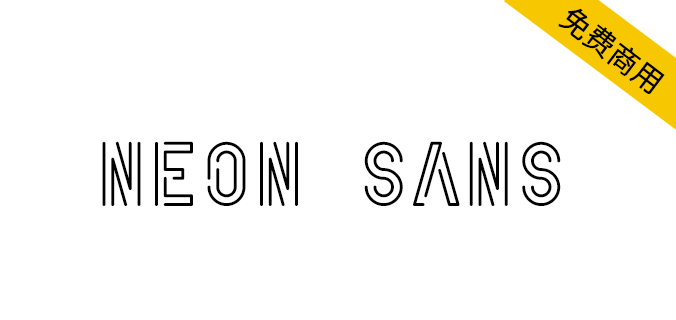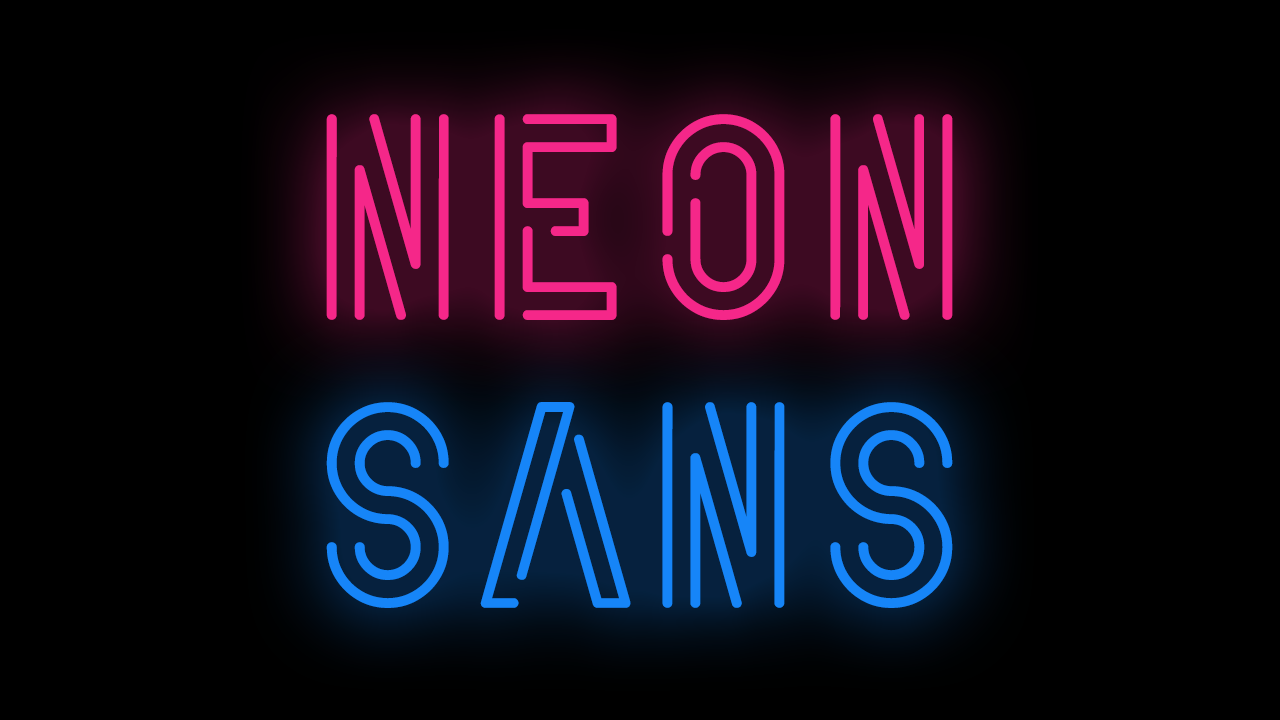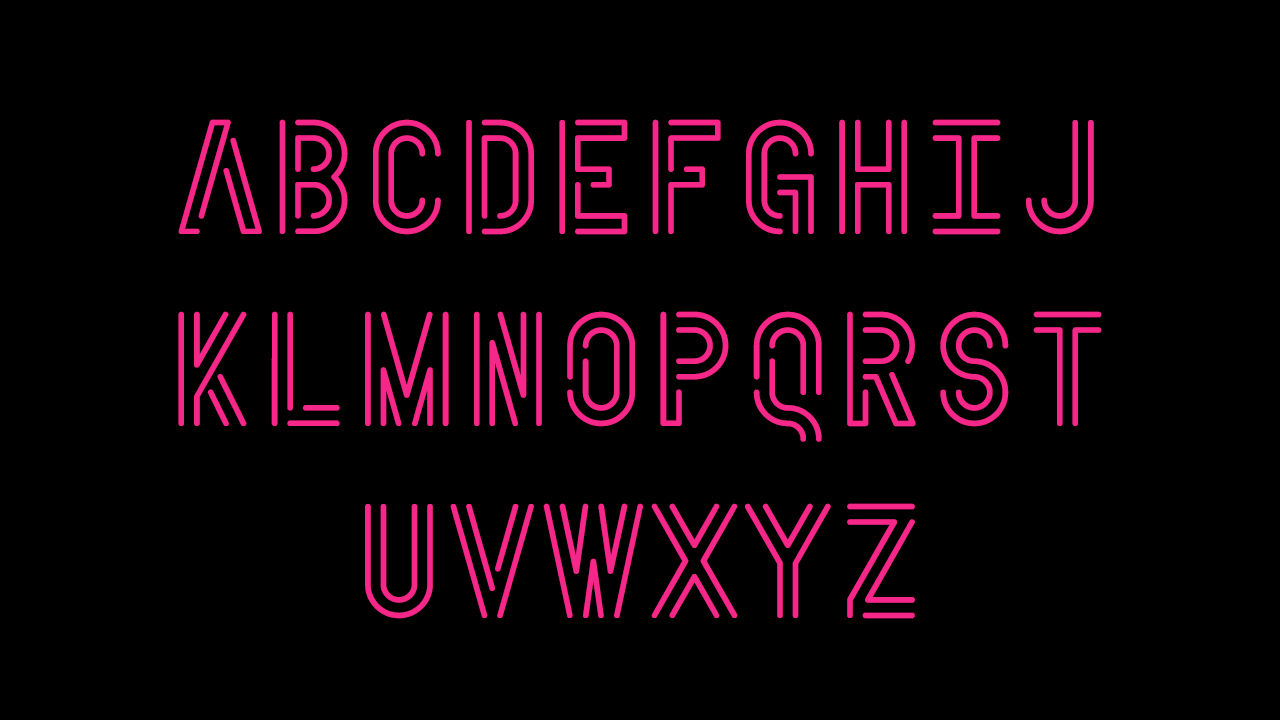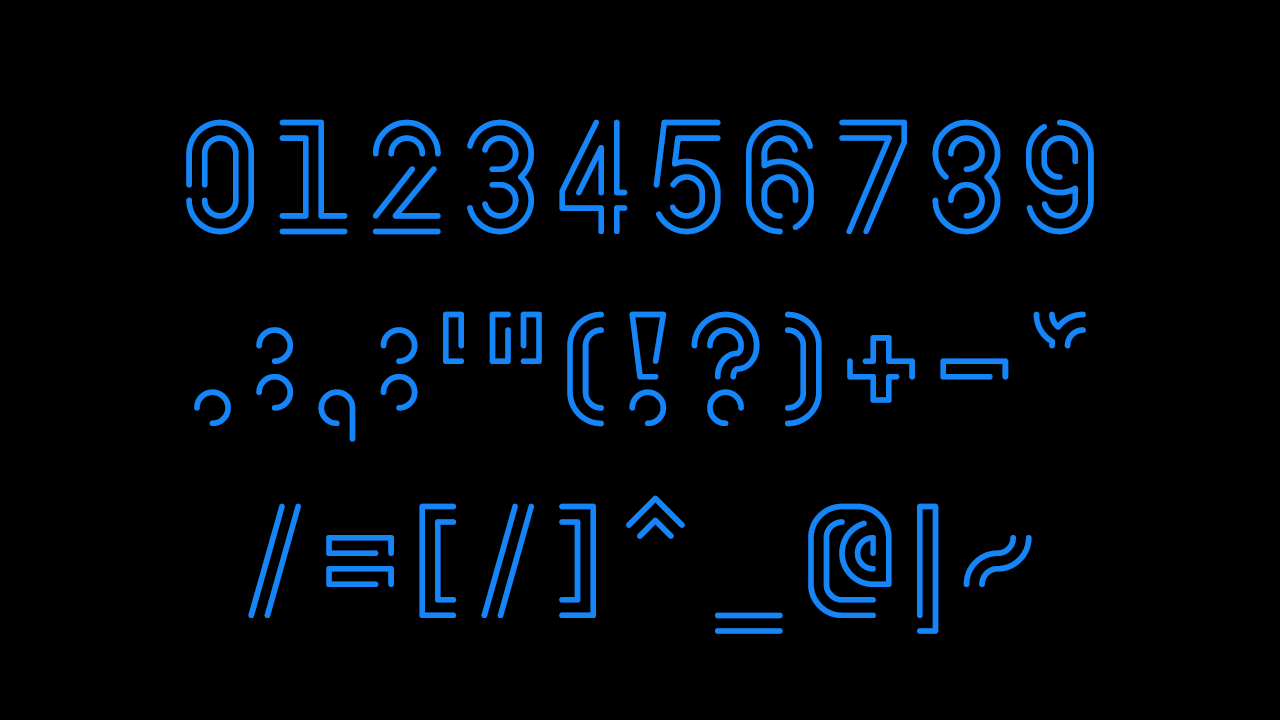
Neon Sans是一款根据SIL OFL协议发布的免费商用英文字体,适合配合发光效果的装饰字体,含 417 个字形,支持 78 种语言(南非荷兰语、阿尔巴尼亚语、阿斯图里亚斯语、阿苏语、巴斯克语、本巴语、贝纳语、布列塔尼语、奇加语、康沃尔语、捷克语、荷兰语、恩布语、英语、世界语、爱沙尼亚语、菲律宾语、芬兰语、弗留利语、加利西亚语、古西语、匈牙利语、伊博语、印度尼西亚语、爱尔兰语、意大利语、Kabuverdianu、Kalenjin、Kamba、Kikuyu、Kinyarwanda、拉脱维亚语、Luo、卢森堡语、Luyia、Machame、Makhuwa-Meetto、Makonde、马达加斯加语、Manx、Meru、Morisyen、North Ndebele、Nyankole、Oromo、葡萄牙语、普鲁士语、盖丘亚语、罗马尼亚语, Romansh, Rombo, Rundi, Rwa, Samburu, Sango, Sangu, 苏格兰盖尔语, Sena, Shambala, Shona, 斯洛伐克语, Soga, 索马里语, 西班牙语, 斯瓦希里语, 瑞典语, 瑞士德语, Taita, Teso, 土耳其语, 乌兹别克语 (拉丁语),沃拉普克语、文乔语、瓦尔泽语、威尔士语、西弗里斯兰语、约鲁巴语、祖鲁语。)